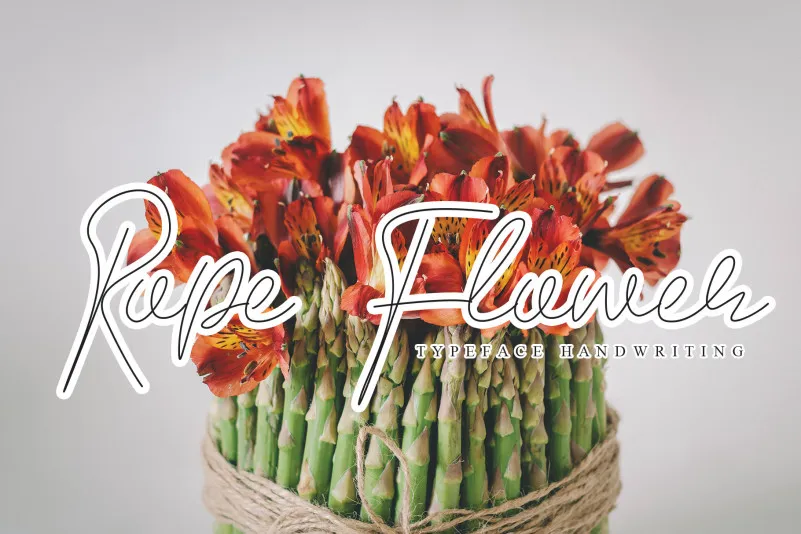
Rope Flower Script Font – Download Grátis
A fonte ‘Rope Flower Script Font’ é uma elegante e delicada escrita a mão que combina elementos florais com a aparência de fios suaves. Perfeita para adicionar um toque autêntico aos seus projetos gráficos, especialmente na categoria das cartas agradecimento, convites de casamento, cartões de felicitações e logotipos. Suas ondulações delicadas e linhas finas fazem dela uma escolha perfeita para qualquer design que precise de um toque pessoal. Esta fonte é ideal tanto para impressão em cores quanto preto e branco, tornando-a versátil o suficiente para atender a todos os seus projetos criativos. Engajante por sua sofisticação e elegância, ‘Rope Flower Script Font’ é um recurso gráfico indispensável para qualquer designer que busca adicionar uma sensação de humanidade a suas criações.